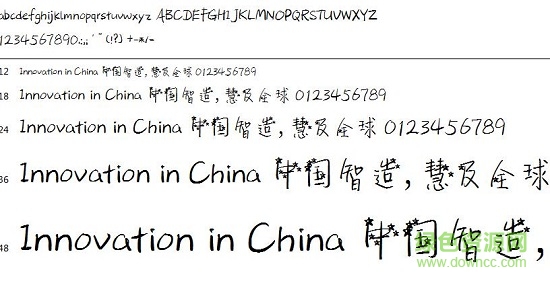
繁星下午茶字體是一款充滿夢(mèng)幻色彩的字體,這款字體每個(gè)字都被星星包裹著,顯得非常的俏皮,有喜歡的朋友歡迎來綠色資源網(wǎng)下載!
繁星下午茶字體是一款根據(jù)經(jīng)典的下午茶字體經(jīng)過加工之后得到的藝術(shù)字體,這款字體在繼承的下午茶字體的基礎(chǔ)之上,在每個(gè)字的邊角都加上了一些星星,看上去更加酷炫!